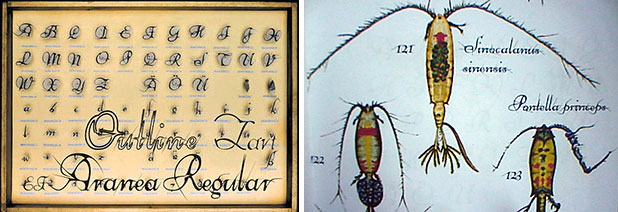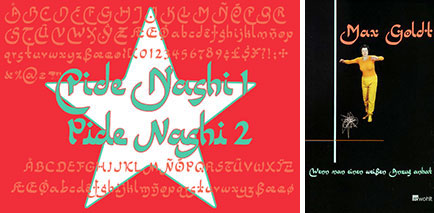
Verena Gerlach - Schriften des AlltagsMeist sind es typografische Fundstücke, die Verena Gerlach zum
Schriftentwerfen inspirieren: alte Stempel, Straßenschilder,
Plastikbuchstaben. Die Berliner Designerin beherrscht die Typo-Klaviatur aus dem
Effeff. Ihr typografisches Œuvre gehört zu den vielfältigsten der
Schriftentwerferszene. Weiterlesen ...
![]() Verena Gerlachs Lebenslauf in Kurzform:
geboren 1971 in Berlin. Grafikdesignerin, Typedesignerin und Typografin. 1993 - 1998 Studium Kommunikationsdesign an der Kunsthochschule Berlin-Weißensee. Seit 1999 selbständig als Grafikdesignerin und Typografin mit eigenem Büro in Berlin tätig. Verena Gerlachs typografisches Repertoir reicht von 8 pt über 4cm2 bis zu 2400m3. ![]() Verena Gerlach FF City Street Type: die Straßenschriften der geteilten Stadt ![]() In Berlin prägten über Jahrzehnte zwei unterschiedliche Straßenschild-Systeme das Erscheinungsbild von West und Ost. Die West-Variante geht auf Groteskschriften des Berlins der 30er Jahre zurück, im Osten bediente man sich einer 50er-Jahre-Grotesk mit technischer Ausprägung. Ole Schäfer und Verena Gerlach haben die Schrifttypen anhand der Originalschilder recherchiert, also nicht auf Vorlagen zur Schilderherstellung zurückgegriffen. So entstanden aus den im Straßenbild verwendeten Ausprägungen für den Ostteil zwei, für den Westteil eine Originalschrift. Um die Schriften alltagstauglich zu machen, haben die beiden Schriftentwerfer die in Straßenschildern nicht vorkommenden Zeichen neu entworfen und stilistisch angepaßt. Zusätzlich haben sie zu den Schrifttypen je eine Headlineschrift entworfen, die mit den Strichstärken Regular, Medium und Bold für typografisches Arbeiten bestens geeignet sind. Wer mit der ziemlich weit verbreiteten DIN-Schrift unzufrieden ist bzw. an Grenzen stößt, den werden die 9 Schriftschnitte der FF City Street Type glücklich machen, die sogar Tabellenziffern, Expert-Sets mit Pfeilen und andere nützlichen Zeichen mitbringen. Figurenverzeichnis FF City Street Type West (auf Verena Gerlachs Webseite) Figurenverzeichnis FF City Street Type East (auf Verena Gerlachs Webseite) FF City Street Type, alle Schnitte und Probe setzen (FontShop Webseite) FF Karbid: von der Mauer abgelauert ![]() Die Vorlage für FF Karbid entstammt einer alten Berliner Fassadenbeschriftung. Die formalen Eigenheiten der Vorlage sind in den Buchstaben der Display-Schnitte noch gut zu erkennen (zum Beispiel im Buchstaben g mit seinem verkürzten, krummen Schweif). Zugunsten der Lesbarkeit sind die Buchstabenformen in den Textschnitten vereinfacht. Verena Gerlach ist es gelungen, durch Reduzierung aus einer reinen Display-Schrift im Stil der 30er Jahre eine eigenwillige, aber sehr gut lesbare Textschrift herzuleiten. Damit eröffnet das FF Karbid-Gesamtpaket außergewöhnliche und prägnante typografische Gestaltungsmöglichkeiten. Figurenverzeichnis FF Karbid Display (auf Verena Gerlachs Webseite) Figurenverzeichnis FF Karbid (auf Verena Gerlachs Webseite) FF Karbid, alle Schnitte und Probe setzen (FontShop Webseite) Linotype Pide Nashi: multikulturell ![]() Auf den ersten Blick sehen Texte, gesetzt in Pide Nashi, wie arabische oder indische Texte aus. Auf den zweiten erkennt man sofort unsere vertrauten Buchstaben. Verena Gerlach wollte keine »verkleidete Schrift« schaffen, sondern sie ließ sich bei Entwerfen der lateinischen Buchstaben von den Pinselschriften asiatischer Kulturen inspirieren: Abstriche entgegen der Schreibrichtung, ausladende Unterlängen, Punkte in den Versalien. Pide Nashi ist überall dort angebracht, wo das Aussehen »westlicher Schreibschriften« zu »normal« wirkt. Ihren ersten öffentlichen Auftritt hatte die Schrift 2002 auf dem Titel der Max-Goldt-Erstausgabe »Wenn man einen weißen Anzug anhat« (Abbildung oben rechts). Figurenverzeichnis Pide Nashi (auf Verena Gerlachs Webseite) Pide Nashi, alle Schnitte und Probe setzen (FontShop Webseite) EF Aranea: typografischer Gliederfüßler ![]() Kaum jemand weiß, dass Verena Gerlach mit Ihrer Schrift Aranea im April 1998 beim Adobe European Design Contest einen Hauptpreis gewann. Der Fontblogger saß damals in der Jury und kann sich genau an die Beurteilung erinnern. Uns gefiel natürlich die Präsentation: Schriften wie Insekten aufspießen bzw. sie zusammen mit den Abbildungen von Insekten zu präsentieren. Bei genauerem Hinsehen erkannten wir die Qualität der Schrift. Es gab zu dieser Zeit viel Vergleichbares, aber Aranea hatte einfach das gewisse Etwas, und deshalb musste das Talent ihrer Entwerferin belohnt werden. Figurenverzeichnis EF Aranea (auf Verena Gerlachs Webseite) EF Aranea, alle Schnitte und Probe setzen (FontShop Webseite) PTL Touja Sans: für Illustrationen und Comics geeignet ![]() Die Vorlagen für die ersten Touja-Buchstaben fand Verena Gerlach auf einem alten DDR-Stempel aus den 50er Jahren. Hieraus entwickelte sie eine eigenwillige kursive Headline-Familie, eine Mischung aus Schreib- und Schablonen-Schrift: man beachte die offenen Formen in den Gemeinen, zum Beispiel dem o und dem e. Der Charme der 50er Jahre blieb erhalten, ohne dass die Schrift altbacken wirkt. Es gibt Touja in einer Sans- und einer Slab-Version mit jeweils vier Strichstärken. Bei den Ziffern können Anwender zwischen Mediäval- und Versalziffern wählen. Touja eignet sich hervorragend als Plakat- und Headlineschrift, dabei verträgt sie sich bestens mit Illustrationen. Figurenverzeichnis PTL Touja Sans (auf Verena Gerlachs Webseite) Figurenverzeichnis PTL Touja Slab (auf Verena Gerlachs Webseite) PTL Touja Sans, alle Schnitte und Probe setzen (FontShop Webseite) PTL Touja Slab, alle Schnitte und Probe setzen (FontShop Webseite) PTL Trafo: elektrisierend ![]() PTL Trafo ist eine schmale Headlineschrift mit handgezeichnetem Charakter. Sie zeigt die Rauheit der Pinselbuchstaben, wie man sie auf alten Elektroschränken vorfindet. Trafo ist in drei verschiedenen Beschriftungsstilen lieferbar: Full, Outline und Shadow, alle mit Expertsets die zusätzliche Sonderzeichen bieten. Figurenverzeichnis PTL Trafo (auf Verena Gerlachs Webseite) PTL Trafo, alle Schnitte und Probe setzen (FontShop Webseite) PTL Lore: ornamentale Schablonenschrift ![]() Eine Schablonenschrift aus den 60er Jahren stand Pate beim Entwurf von PTL Lore. Aufgrund ihrer geometrischen Konstruktion wirkt sie zunächst industriell; organische Formen relativieren diesen Eindruck, so dass sich das Schriftbild von Lore als ausgesprochen sympathisch darstellt, geradezu ornamental. Lore ist für den Einsatz im Headline-Bereich gedacht. Es gibt sie in Regular, Medium, Bold plus den dazugehörigen Expertsets Figurenverzeichnis PTL Lore (auf Verena Gerlachs Webseite) PTL Lore, alle Schnitte und Probe setzen (FontShop Webseite) PTL Tephe: fliegende Büroraumbeschriftung ![]() PTL Tephe ist eine Hommage an die handgeschnittenen Plastik-Steckbuchstaben der Mieterindextafeln (»Stummer Portier«) in DDR-Bürohäusern. Die durch die Technik bedingte Form der Buchstaben nahm Verena Gerlach in die Digitalfassung auf. Zwei Tephe-Versionen bilden eine Schriftkleinfamilie: Als Steckbuchstaben mit Führungsleiste und als Buchstaben ohne Unterlinie, also so, wie sie der Betrachter auf einem Stummen Portier sehen würde. Figurenverzeichnis PTL Tephe (auf Verena Gerlachs Webseite) PTL Tephe, alle Schnitte und Probe setzen (FontShop Webseite) Herausgegeben: Mi - August 31, 2005 at 12:36 nachm. | |